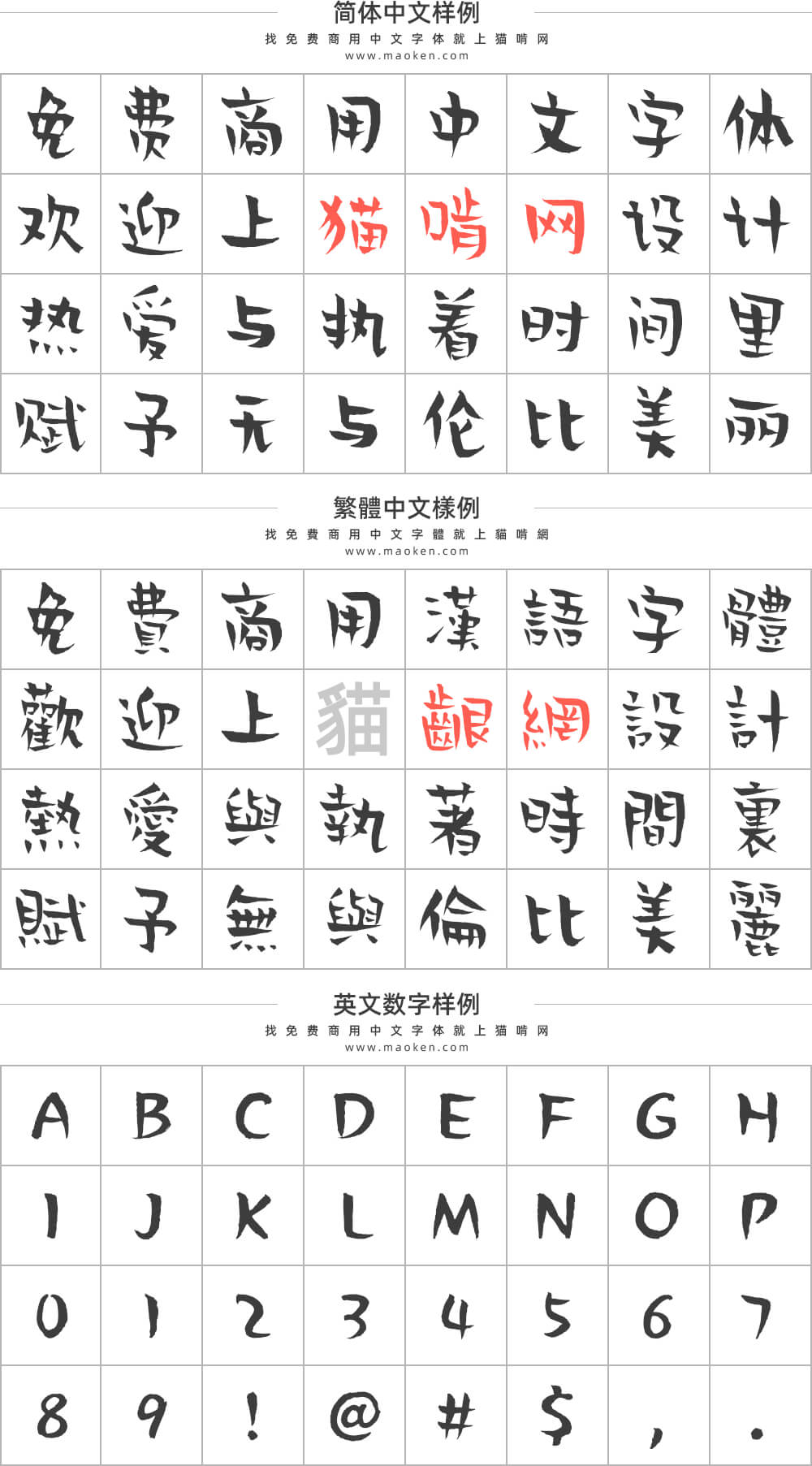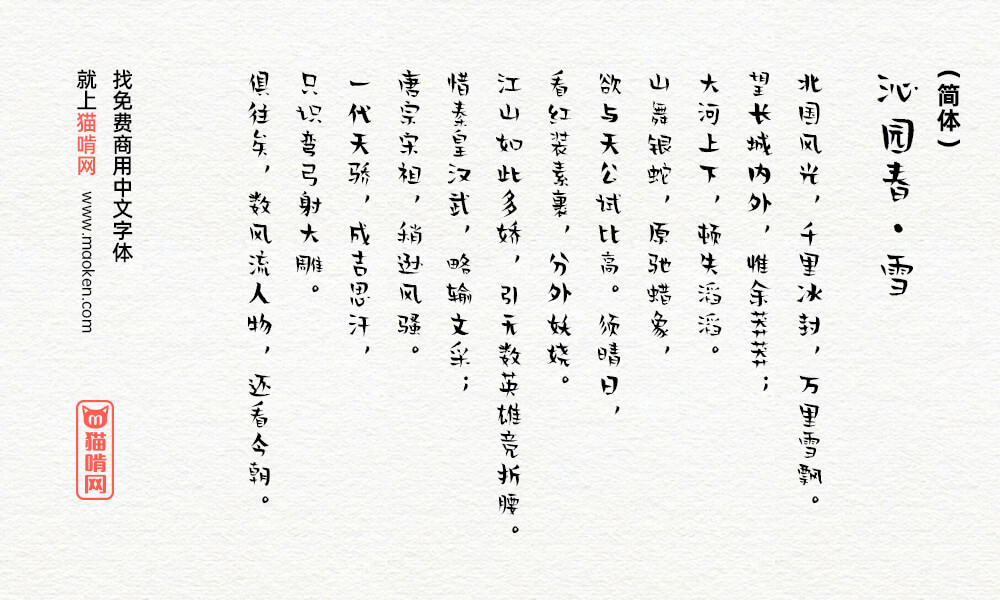
贤二体:汉仪首款商用免费字体佛系上线
字体作者:汉仪字库 (中国大陆) 字体字重:1个
贤二体是北京龙泉寺动漫中心与汉仪字库联合推出的一款商用免费字体。 贤二体的字形偏长,起笔收笔锋利且粗细对比明显,笔画笨拙微带曲线感。字体组合结构松散,重心不稳,达到诙谐幽默,惹人喜爱的效果。
贤二体字形结构和笔画的特点恰好符合贤二小和尚的性格特点,与龙泉寺学诚法师所传达出的:“世俗生活里,人还是二一点比较好”如出一辙。
谁是贤二?
是不二寺的小和尚,一口气能吃十个冰激凌。他很聪明,但是又很懒惰,总是需要师父点拨。师父经常会讲一些饱含哲理的话语,帮助我们排解压力,告诉我们,其实,快乐就是这么简单。